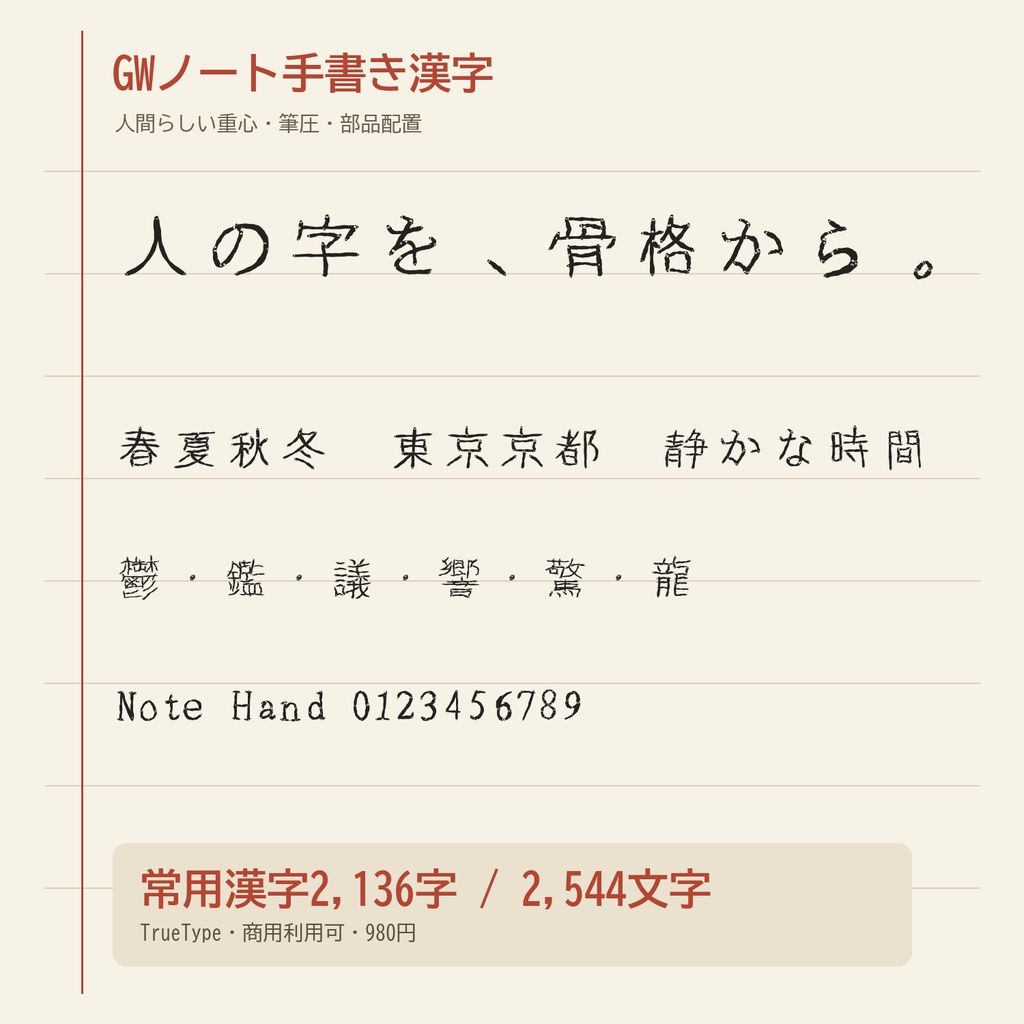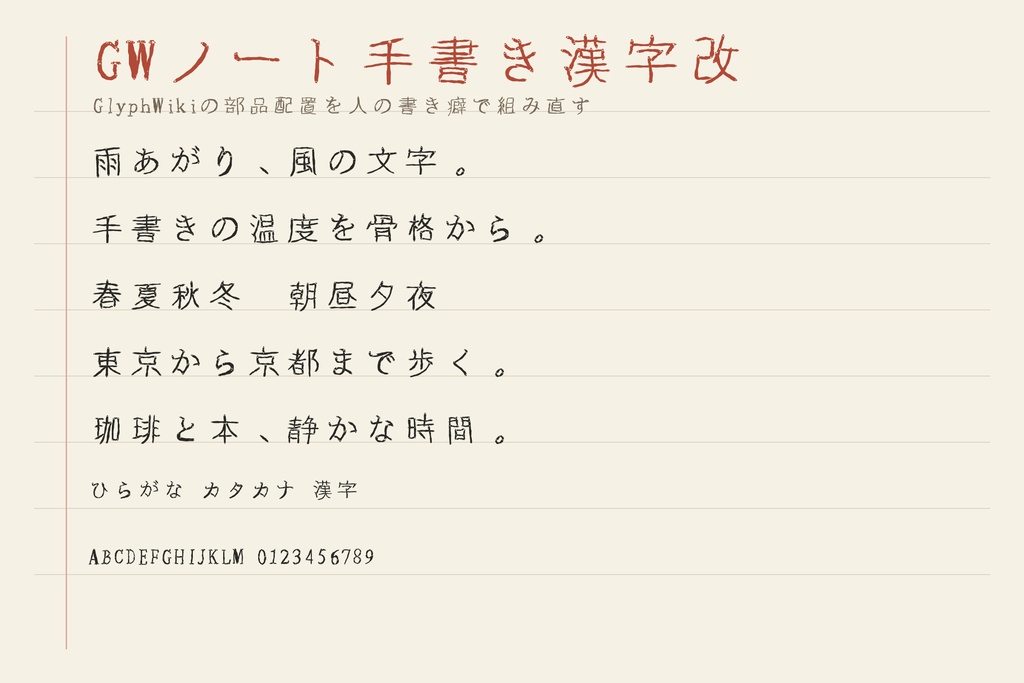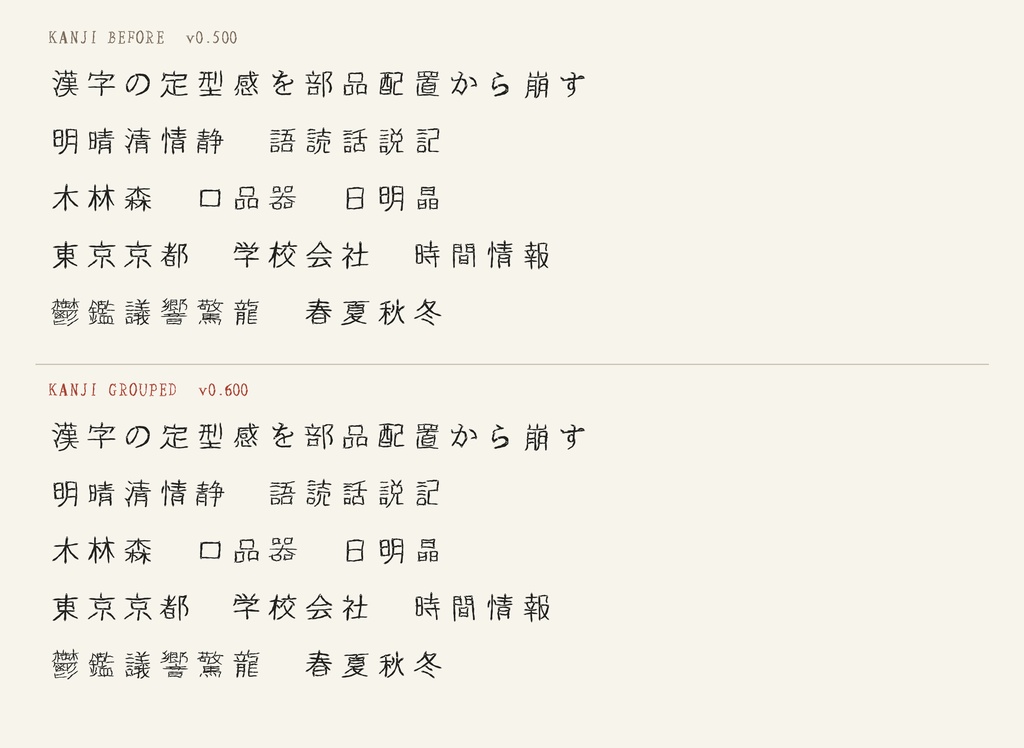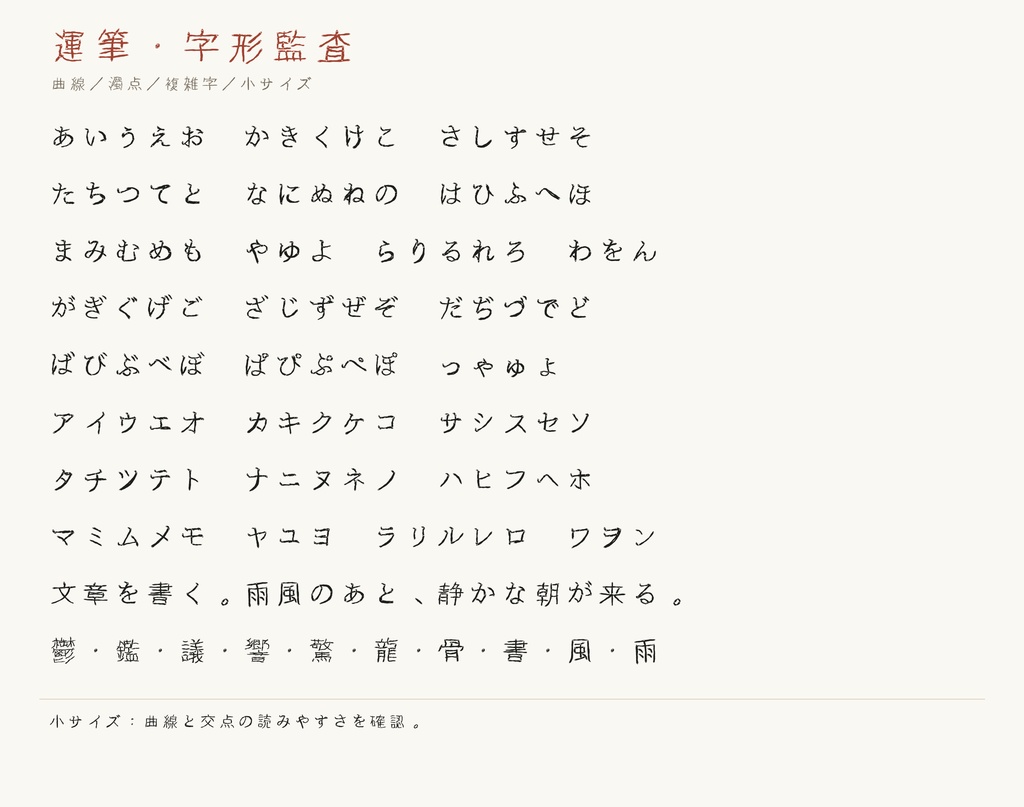
【GWノート手書き漢字】人間らしい日本語手書きフォント|常用漢字2,136字・商用利用可
【GWノート手書き漢字 / GW NOTE HAND KANJI】 GlyphWikiのKAGE骨格を、人がノートへ書く運筆として一画ずつ引き直した 日本語手書きフォントです。 単純な手ぶれ加工ではなく、文字ごとの重心、筆圧、交点、偏・旁・冠・脚の配置、 平行画の間隔、左右非対称な輪郭を決定的に生成しています。 ■ 価格 980円 ■ 形式 TrueType(TTF) / Windows・macOS ■ 収録 2,544文字 ・常用漢字 2,136字 ・ひらがな、カタカナ ・英字、数字、全角英数 ・基本的な日本語約物、記号 ・作品見本用の追加漢字 ■ 特徴 ・漢字は偏・旁などの部品ごとに位置、比率、傾きを変化 ・かなはKAGEの二次・三次曲線を人の運筆として再構成 ・画ごとの筆圧差と、完全には対称でない輪郭 ・同じ入力から同じ字形を再現できる安定した手書き表現 ■ おすすめ用途 ノート風デザイン、日記、手紙、漫画、ゲーム、配信、動画字幕、同人誌、 教材、サムネイル、商品POP、親しみのある見出しや短文 ■ 利用 個人・商用利用可。クレジット不要です。 ロゴ、動画、ゲーム、印刷物、配信、同人・商業作品に使用できます。 フォントファイルの再配布・共有・転売は禁止です。 詳細はZIP内の利用規約をご確認ください。 ■ 無料版について 英字、数字、基本約物、ひらがな、カタカナのみを収録した無料版も公開しています。 無料版も同じ利用規約で商用利用できます。 ※横書きを基準に調整しています。縦書き用字形・縦組みメトリクスは未調整です。 ※同じ文字を入力した場合、字形は毎回同じです。